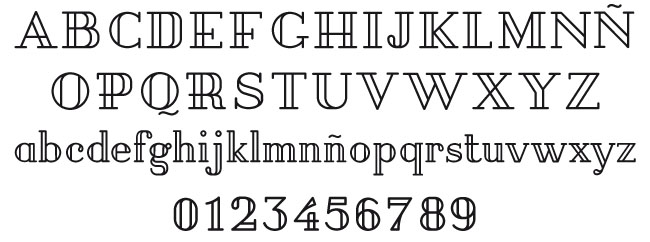
Pirou es una tipografía experimental outline inspirada en la tipografía Didot, con finos trazos y más de 300 glifos, según comenta su autor, Quentin Grébeude. Es una tipografía perfecta para logotipos o isotipos, e incluso titulares y subtitulares, ya que su tamaño permite dicha versatilidad.
Quentin Grébeude es un diseñador y director de arte francés afincado en París, que posee considerable reconocimiento por esta tipografía en páginas como Behance.
Pirou is an experimental outline typeface inspired by Didot font, with fine strokes and more than 300 glyphs, according to its author, Quentin Grébeude. It is a perfect typography for logos or isotypes, and even headlines and subtitles, since its size allows such versatility.
Quentin Grébeude is a French designer and art director based in Paris.